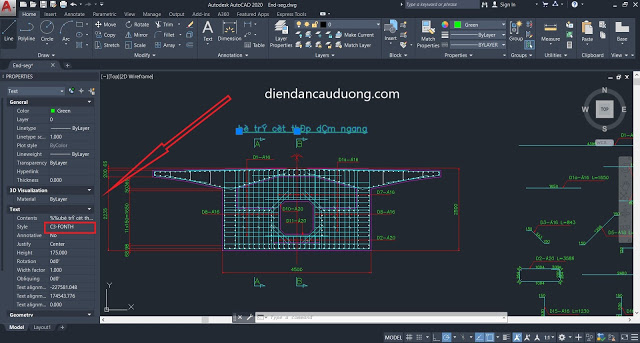
Chào bạn, có phải bạn đang gặp phải một vấn đề rất rất nhiều người dùng AutoCAD đã từng gặp: Lỗi Font chữ tiếng Việt trong bản vẽ CAD? Đừng lo, sau khi đọc bài viết này và làm theo hướng dẫn, vấn đề lỗi Font AutoCAD của bạn sẽ được giải quyết triệt để.
Lỗi font tiếng Việt trong AutoCAD và cách khắc phục triệt để
1. Cách giải quyết khi lỗi font CAD
Nếu bạn đang gặp vấn đề như trên thì 100% Autocad của bạn đang thiếu fonts. Như các bạn đã biết, ngoài các fonts thông dụng như của windows như Unicode, Vni, TCVN3 ….. thì đa số các bản vẽ sử dụng bộ fonts SHX . Ưu điểm của font SHX này là rất phù hợp với bản vẽ kỹ thuật, font đẹp, gọn nhẹ nên hầu hết các đơn vị tư vấn điều sử dụng.
Khắc phục lỗi font chữ trong AutoCAD như thế nào ?
Nếu sau khi cài đặt font bản vẽ vẫn bị lỗi các bạn làm như sau:
B1: Click vào đối tượng bị lỗi, nhấn tổ hợp phím Ctrl + 1. Kiểm tra Style của Text đang sử dụng như hình dưới
B2: Gõ lệnh ST để xem Font chữ còn thiếu, của mình ở đây còn thiếu font C3FontH, nó sẽ có biểu tượng bị lỗi phía trước
B3: Chúng ta chưa vội kiếm Font này. Quay trở lại B1, Click vào Style và rê chuột vào từng style chúng ta đang có, xem có style nào phù hợp hay không. Rất may ở đây có STYLE1 là phù hợp với Font bị thiếu. Chúng ta hãy nhớ tên Style này nhé.
B4: Gõ lệnh ST tìm đến STYLE1 xem kiểu Font ở đây Là VnAvant, hãy nhớ lấy kiểu Font này.
B5: Tìm đến Style Font bị lỗi lúc nãy ( Của mình là C3-FONTH). Thay thế fontname thành VnAvant lấy từ B4.
B6: Nhấn Apply => Close và xem thành quả
Khắc phục lỗi font chữ trong AutoCAD nhanh nhất